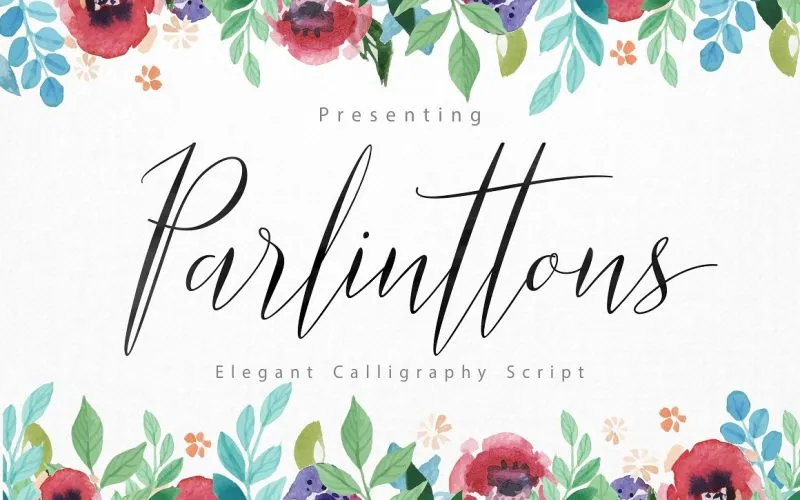
Parlinttons Script Font – Fonte Grátis
Parlinttons Script Font
Esta elegante fonte tipográfica é projetada para transmitir elegância e estilo, com seu traço fino, feminino e agradável. Perfeito para designers profissionais, Parlinttons traz uma mistura de sofisticação natural e suavidade. O Parlinttons pode ser usado em designs de mercado desenvolvidos neste momento, é ideal para estilos como águacolorista, minimalista, moderno e flat design. Se combinado com cores adequadas, você conseguirá criar algo surpreendente que enfeite sua criação. Essa fonte natural e alegre está disponível no estilo de design atual. É perfeito para quem busca uma fonte que seja tanto elegante quanto atemporal. Não hesite em experimentar Parlinttons Script Font, ela certamente fará parte do seu arsenal tipográfico.